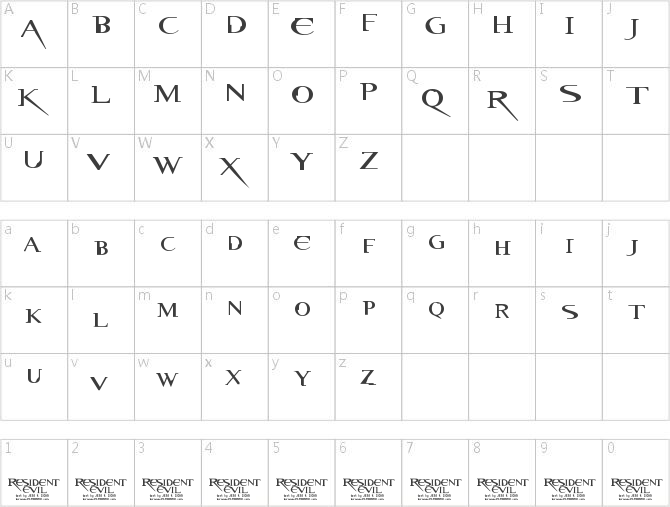
resident evil large 詳情頁(yè)
resident evil large字體字庫(kù)是一款讓人賞心悅目、百看不厭的英文字體,適合各類廣告和產(chǎn)品包裝設(shè)計(jì)應(yīng)用,字體大小0.01MB,格式為ttf字體,上傳用戶是dqq520,作者/版權(quán)方為未知